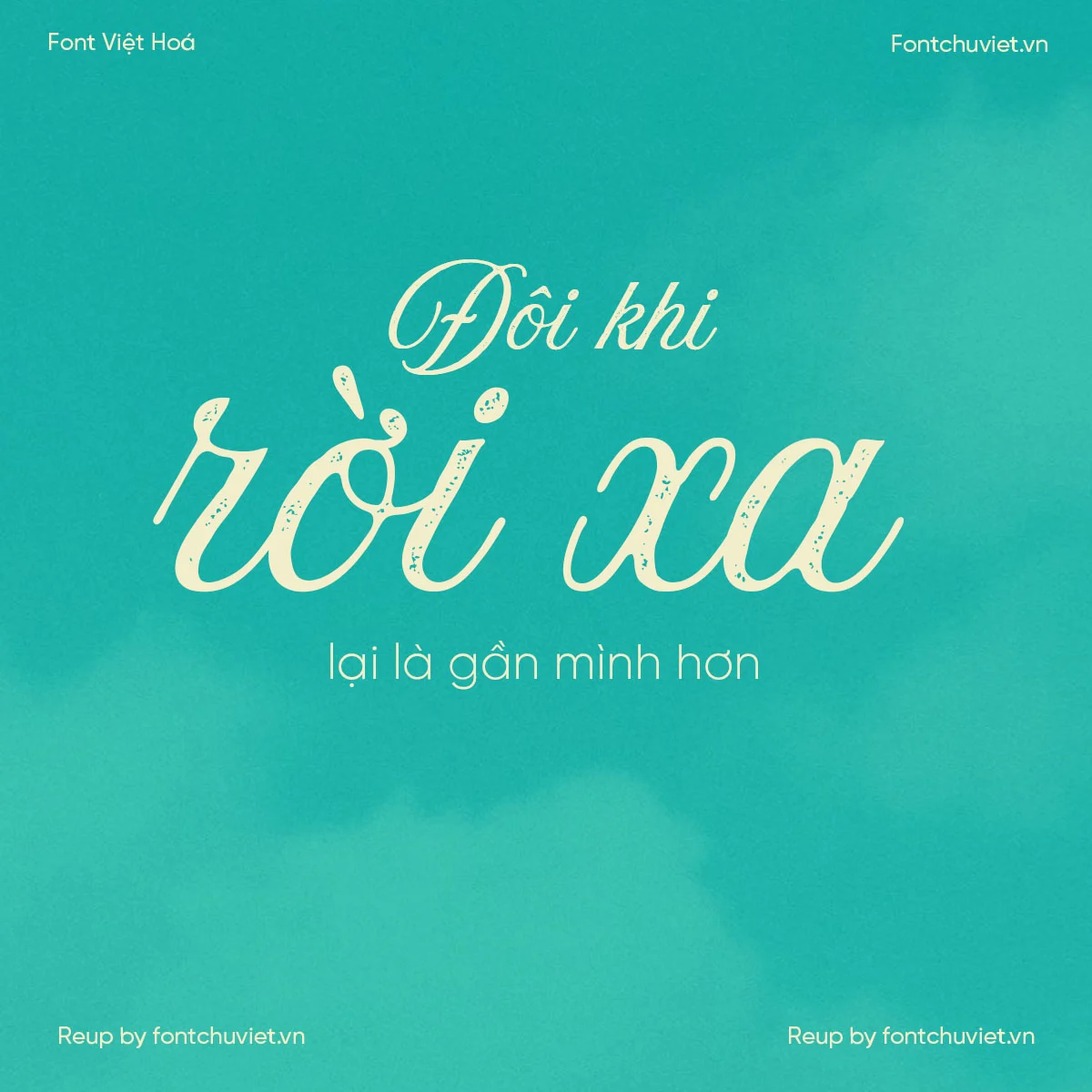
Font VL Aurora Aged – Font Việt hoá
Cỡ chữ: 60px Aa aa AA Thử font Việt hoá 1234567890 0/300 Gõ văn bản bên dưới để xem trước font chữ ◪ View Glyphs Font VL Aurora Aged – Font Việt hoá là một font chữ kiểu viết phấn, phong cách thiết kế chữ nghiêng phù hợp với ghi tên người, sử dụng trong … Đọc tiếp Font VL Aurora Aged – Font Việt hoá